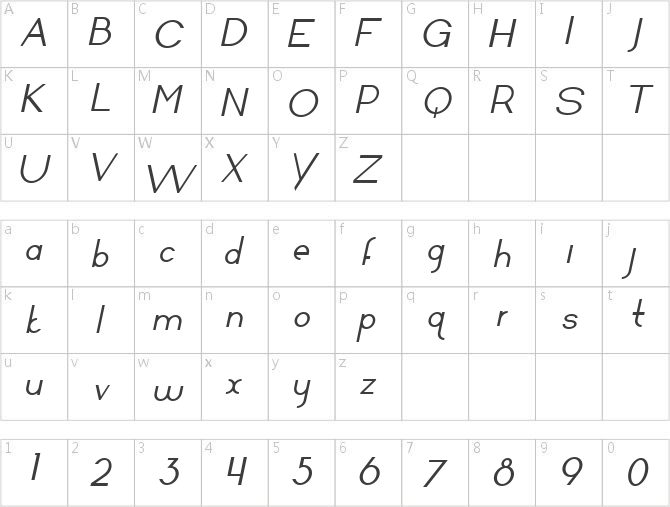
字體名稱: Arrival
Arrivals-and-Departures-Bold-Ita
Arrivals-and-Departures-Bold-Ita字體字庫是一款讓人賞心悅目、百看不厭的英文字體,適合各類廣告和產(chǎn)品包裝設(shè)計應用,字體大小0.04MB,格式為ttf字體,上傳用戶是素年錦時,作者/版權(quán)方為未知